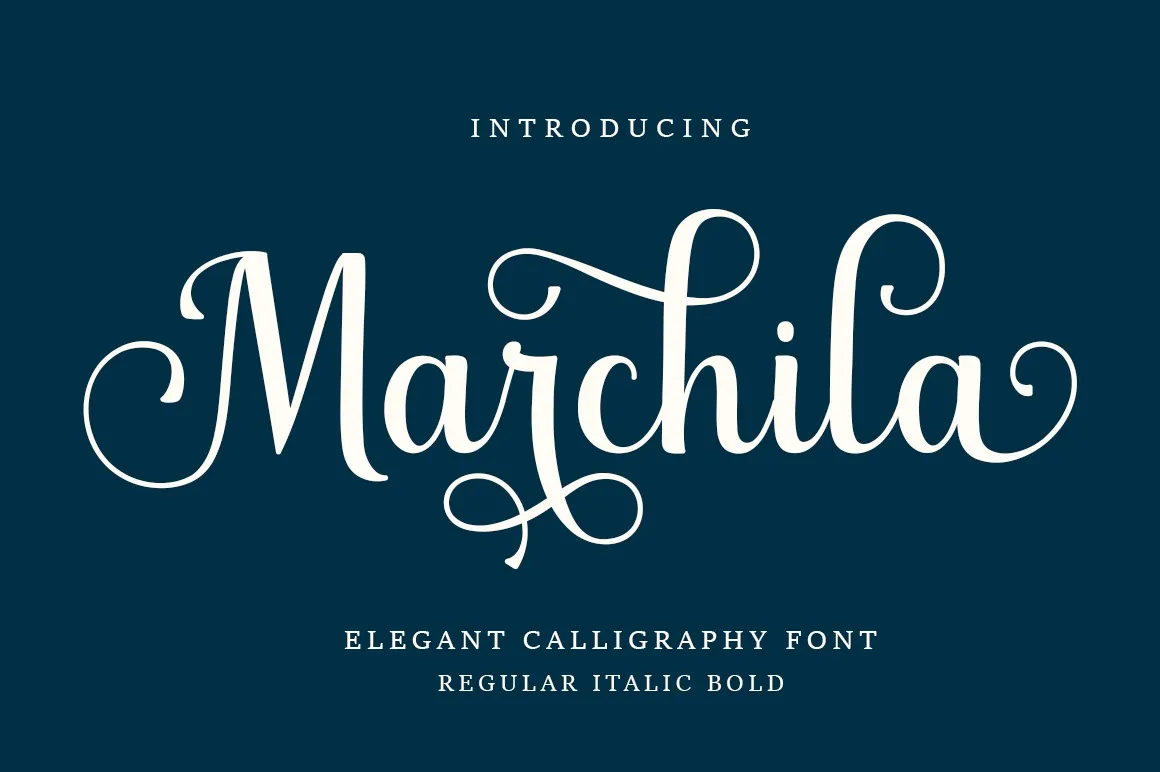
Marchila Font
Marchila Font é uma elegante tipografia script criada pela Manjalistudio, especializada em proporcionar uma aparência moderna ao mesmo tempo que oferece alternativas encantadoras para um visual agradável e renovador. Com sua letra que se move livremente acima e abaixo da linha base, Marchila traz à superfície um toque de magia e originalidade sem deixar de lado a funcionalidade prática. Esta fonte foi projetada especialmente para aqueles que buscam uma nova visão em seus projetos, oferecendo não apenas beleza mas também diversidade com os caracteres PUA codificados. Essa característica permite que você facilmente acesso todos os símbolos e ligaturas incríveis, tornando a criação de design mais divertida e inspiradora sem sacrificar o controle necessário sobre o resultado final. Marchila é uma ótima opção para quem busca um toque especial em qualquer projeto gráfico.